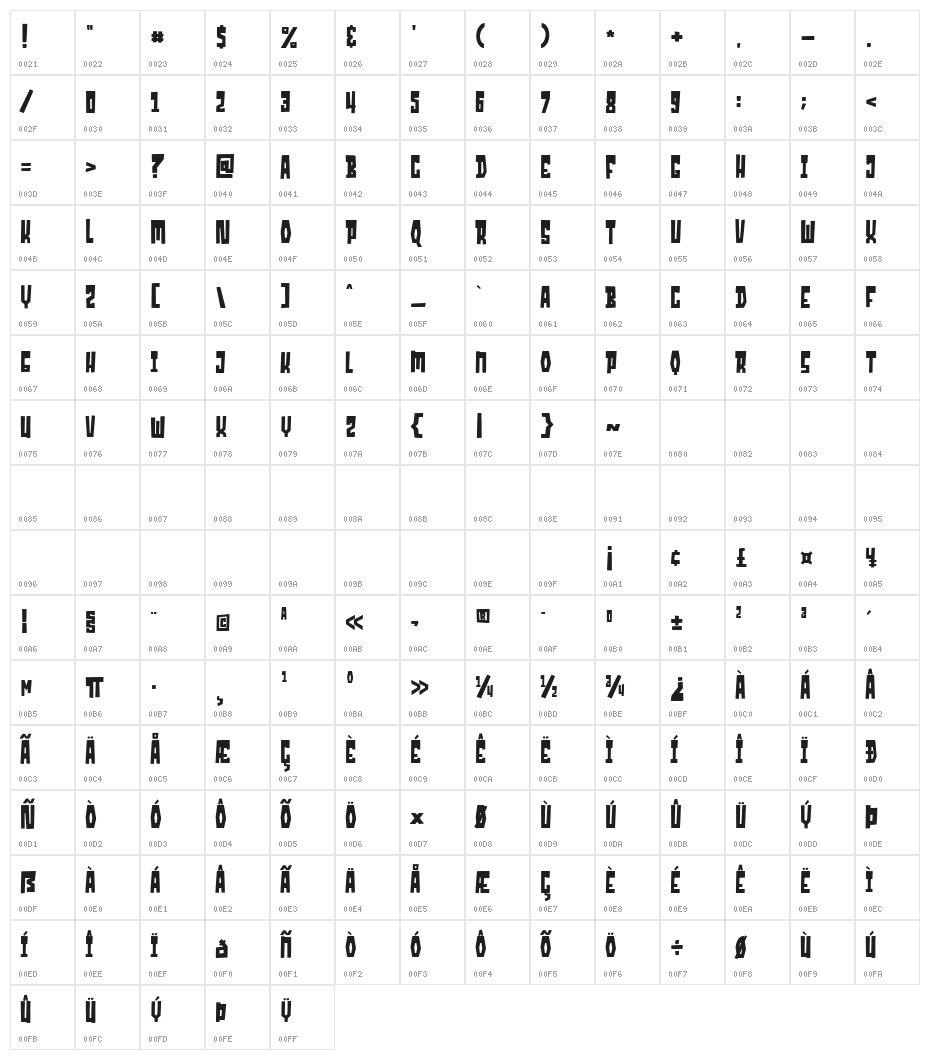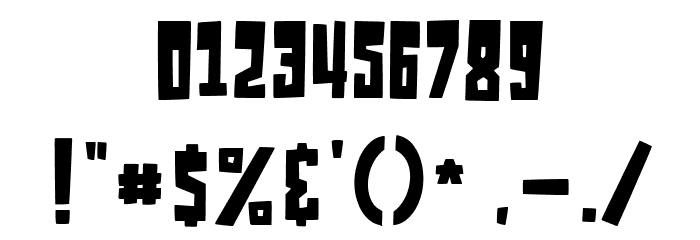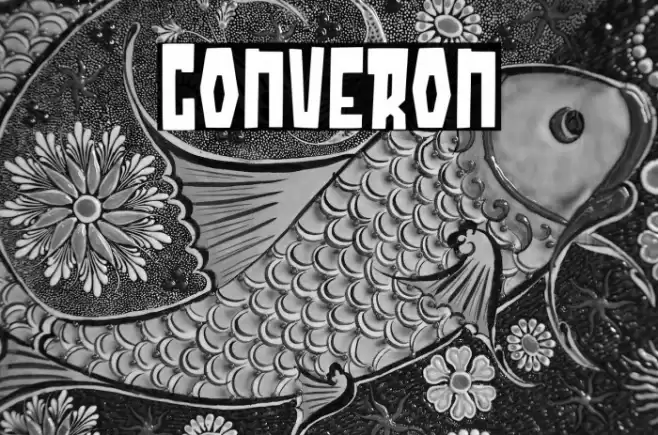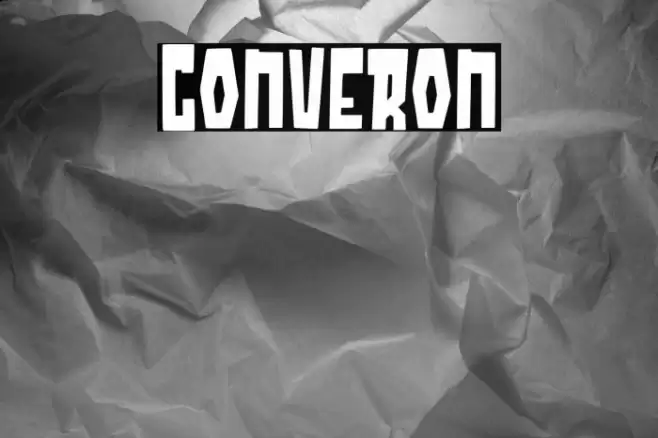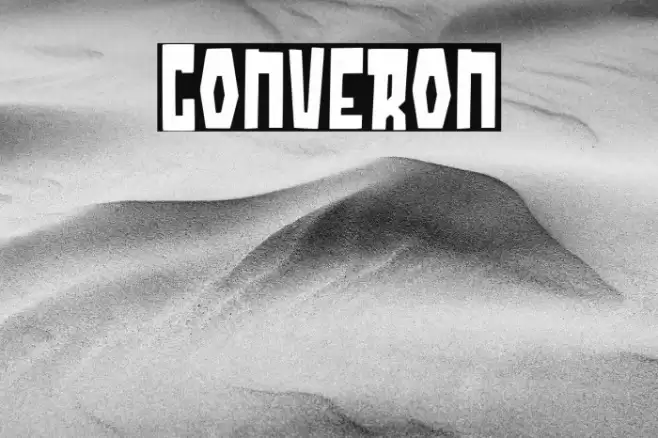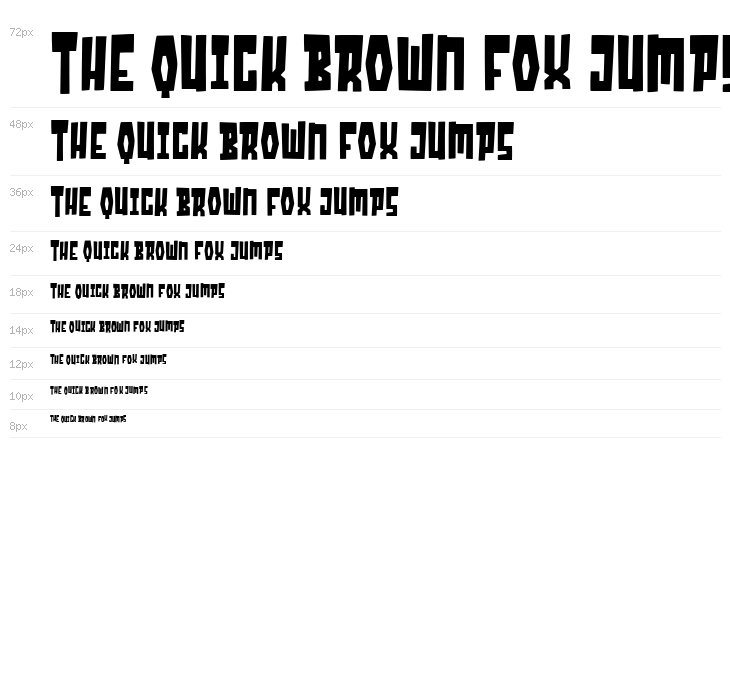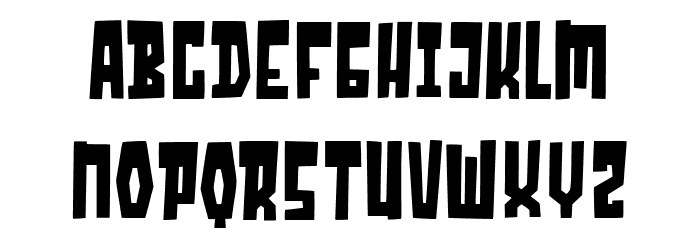
Converon Font
| श्रेणियाँ | Cartoon |
| कंट्रास्ट | High |
| उपयोग का मामला | Headlines, Logos |
| सुझाए गए प्रोजेक्ट | Perfect for posters, album covers, video game titles, and branding that requires a bold statement. |